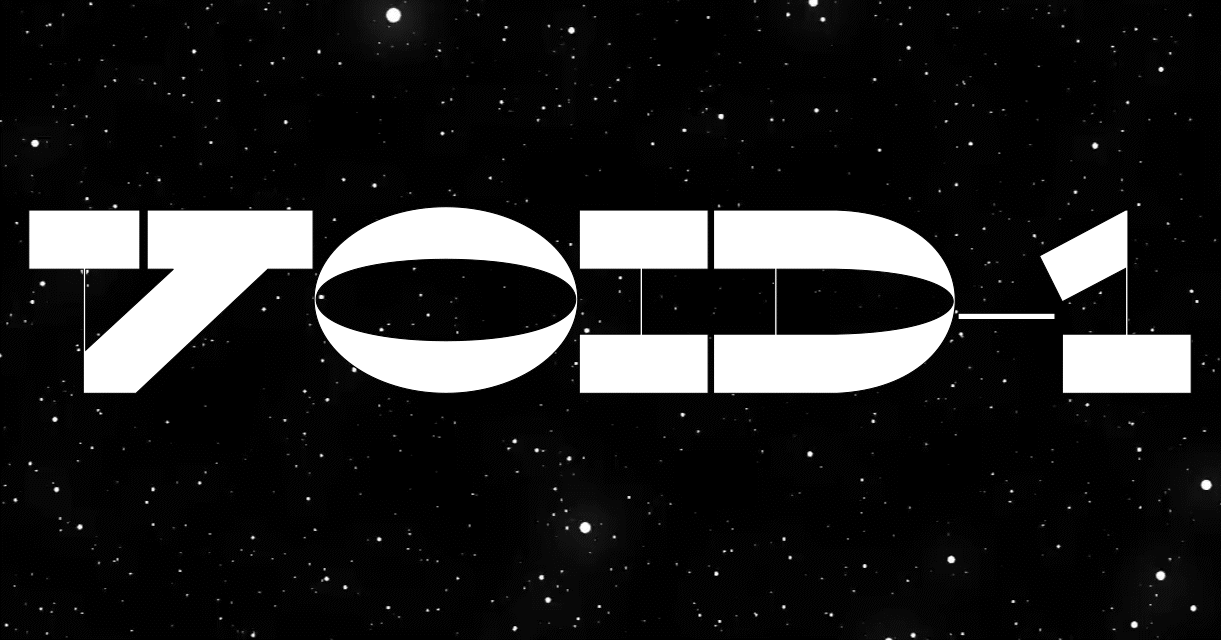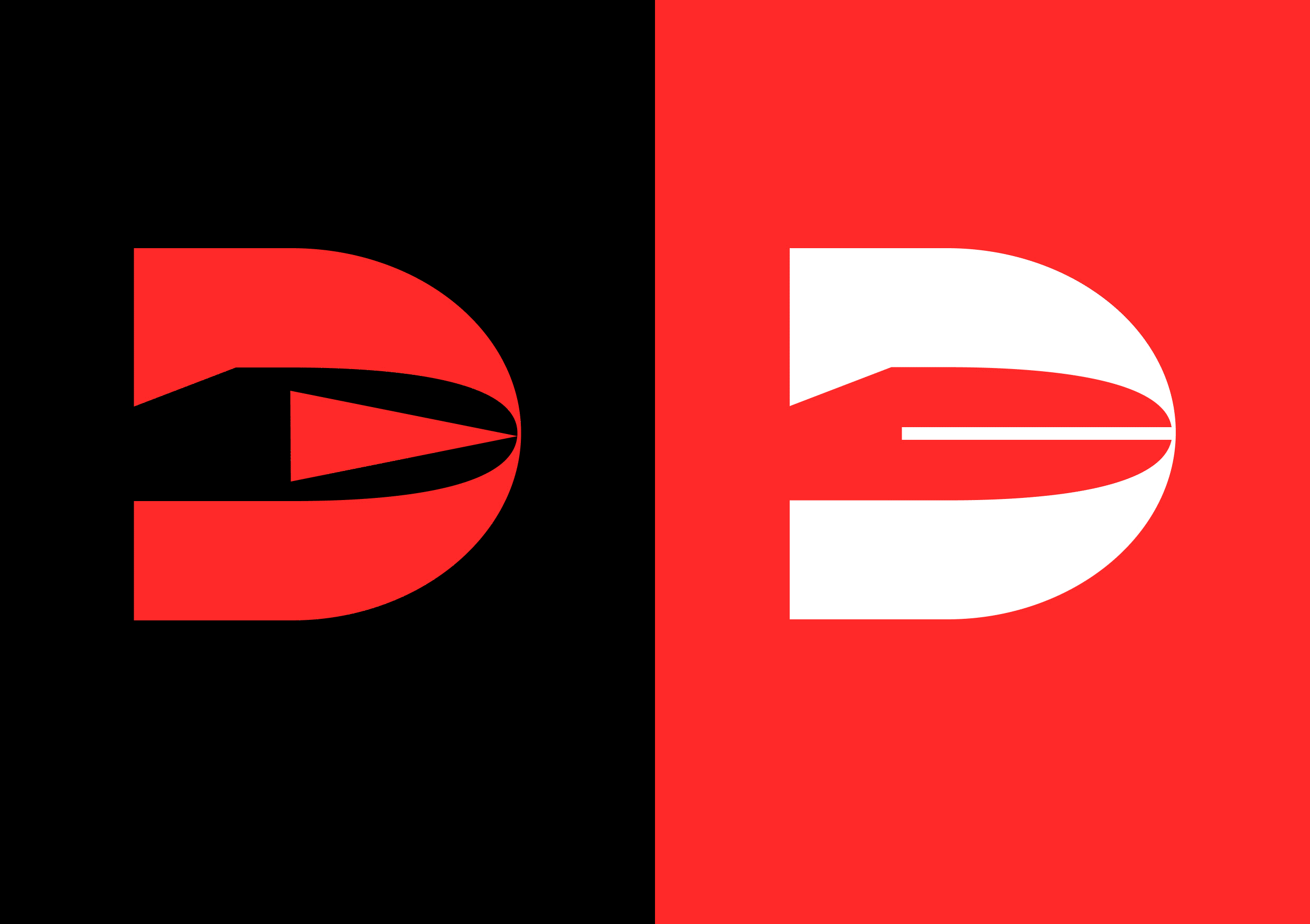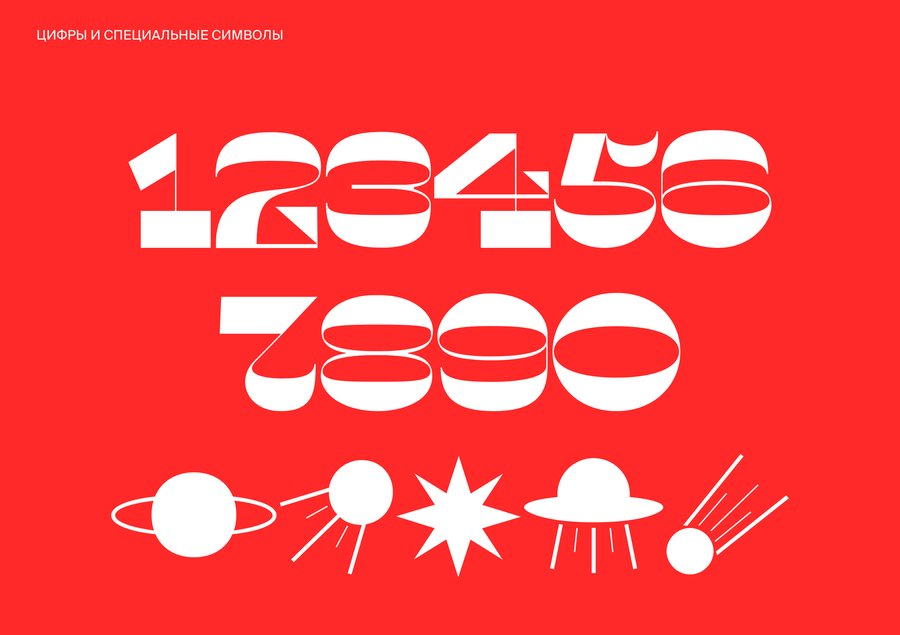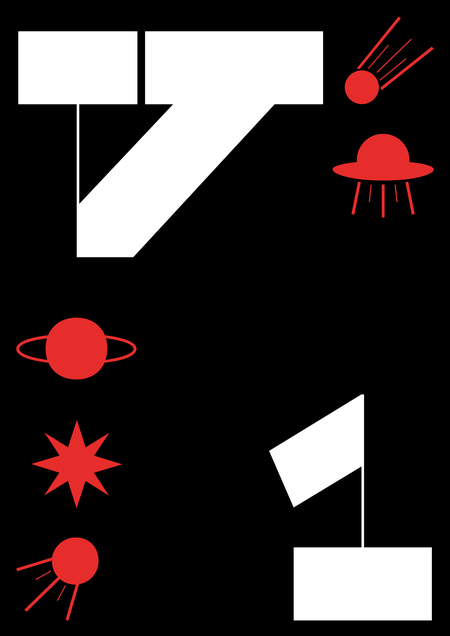
VOID TYPEFACE — это акцидентный шрифт, вдохновением для которого стали итальянские шрифты с обратным контрастом и бескрайние просторы космического пространства.
Прописная и строчная латиница
Прописная и строчная кириллица
Альтернативные формы
Были добавлены OpenType features в виде специальных символов, отражающих характер шрифта. При написании определенных слов их можно добавить в ваш текст